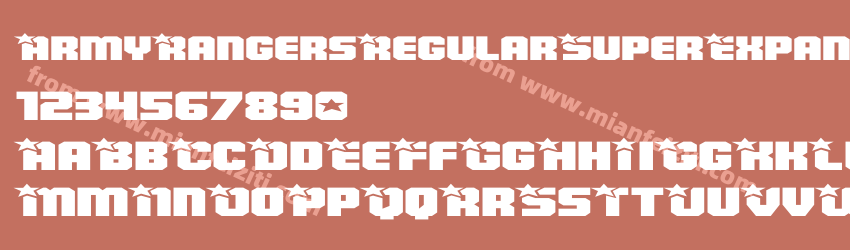
Army Rangers Regular Super Expanded AV5m
字体名称: Army Rangers Regular Super Expanded AV5m
字体字重: Expanded
本款“Army Rangers Regular Super Expanded AV5m”是一款书写很新颖的字体,字体大方,适合各种设计作品使用!欢迎下载!